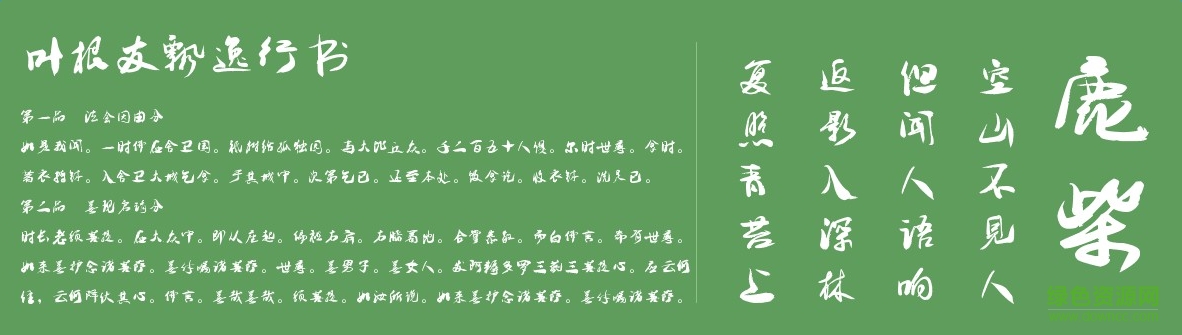
葉根友飄逸行書是一款非常有特色的電腦字體,是葉友根用ipad手寫出來(lái)的一款字體,是將傳統(tǒng)書法與現(xiàn)代科技結(jié)合而產(chǎn)生的一種新的體驗(yàn)作品,感興趣的朋友歡迎來(lái)綠色資源網(wǎng)下載!
葉根友飄逸行書是由葉根友親自設(shè)計(jì)的行書字體,這款字體很有意思,不是用毛筆寫出來(lái)的,是利用ipad手寫版用手指一個(gè)字一個(gè)字的書就,用很多休閑空間的時(shí)候?qū)懗?,字里行間是不是流露出一種親切溫暖的手感和高科技的融合感呢?葉根友飄逸行書的主要筆畫體現(xiàn)在筆畫的尾部,都是自由飄逸出去,如大鵬展翅,自由延伸。